输入名字,挑一个风格,下载 PNG。就这么简单,大约十秒钟。
这些全部出自同一个海绵宝宝字体生成器,只是从列表里换了不同的风格。什么都不用装,也不用注册。
怎样做出海绵宝宝文字
第 1 步:输入名字
打开生成器,把示例文字换成你要的内容:名字、派对主题、频道名、标题。你一边输入,字母就一边重绘。
第 2 步:挑一个风格
剧集风格就是那种黄色海绵质感,带气孔和粗重的深色描边。这是大家脑中的样子,也是这组里最张扬的一个。「样式」标签可以分别调整填充、描边和阴影:字形不变,把音量调小。
第 3 步:选择尺寸
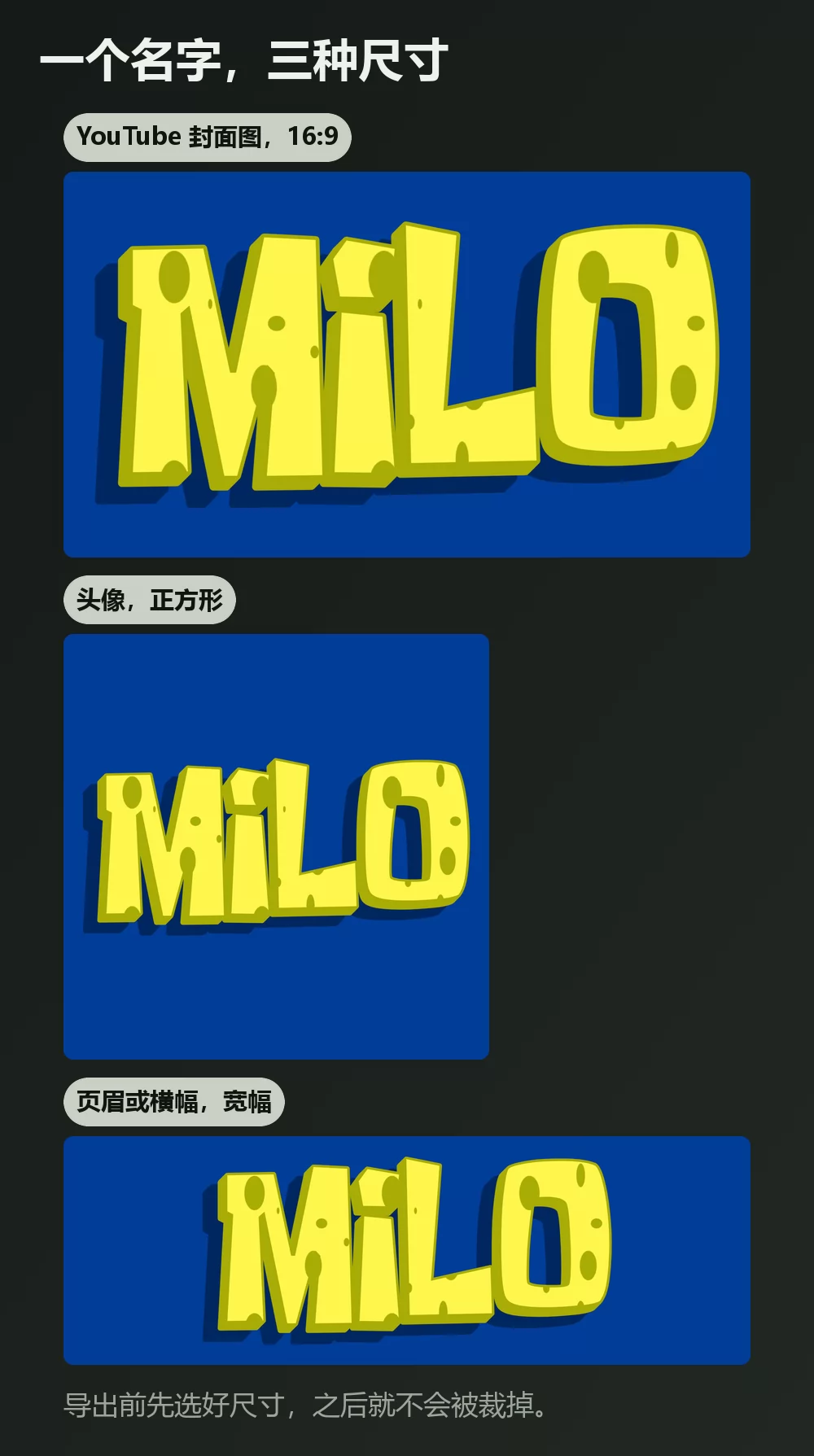
导出前先定好尺寸,之后就不会被裁掉。视频封面用 16:9,头像用正方形,派对横幅用宽条。
第 4 步:下载
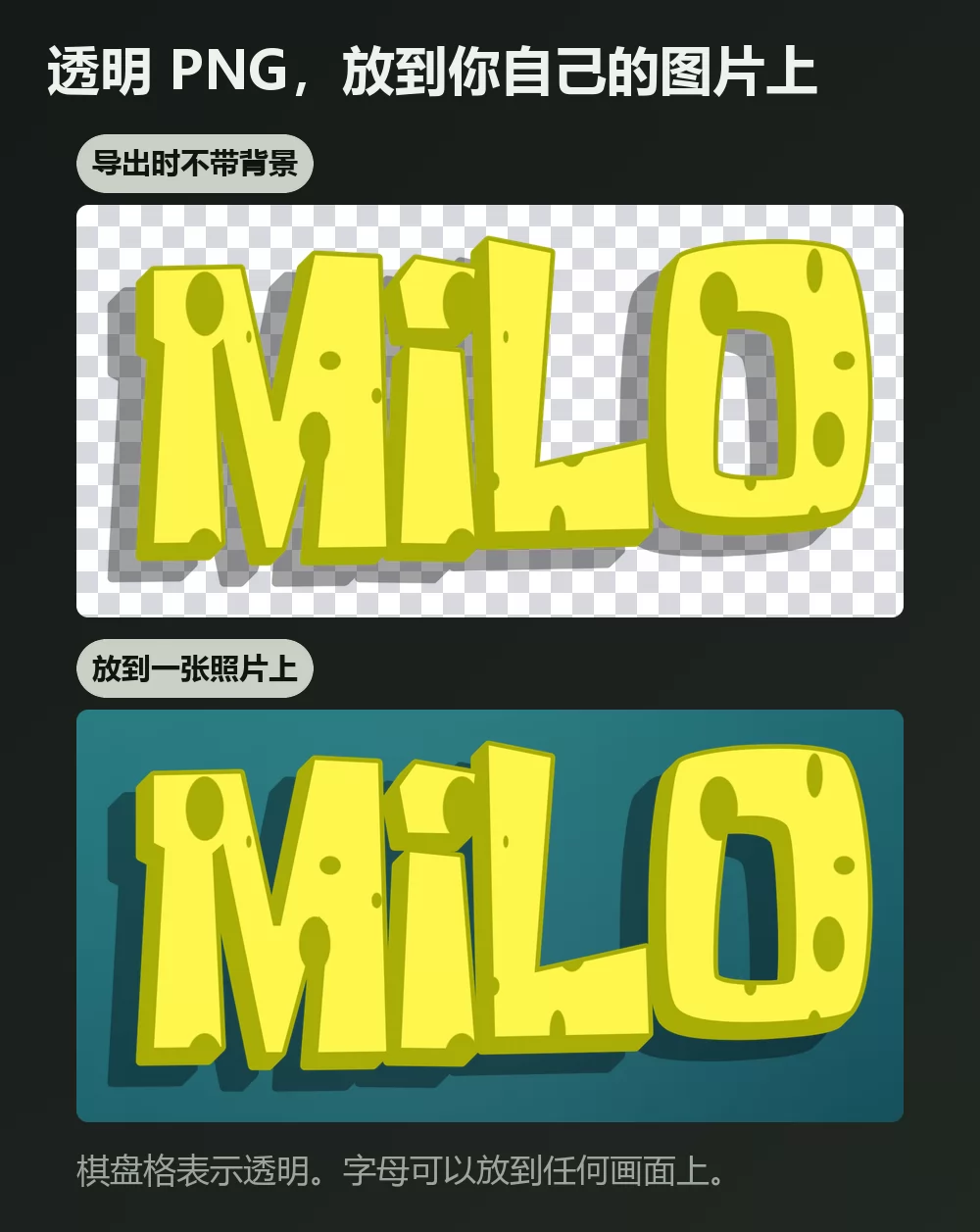
在「下载」标签里选透明 PNG,如果你打算把字母放到自己的照片、截图或邀请函上。这是大多数人漏掉的选项,也正是它让成品看起来是做出来的,而不是贴上去的。
名字一长,很快就占满宽度
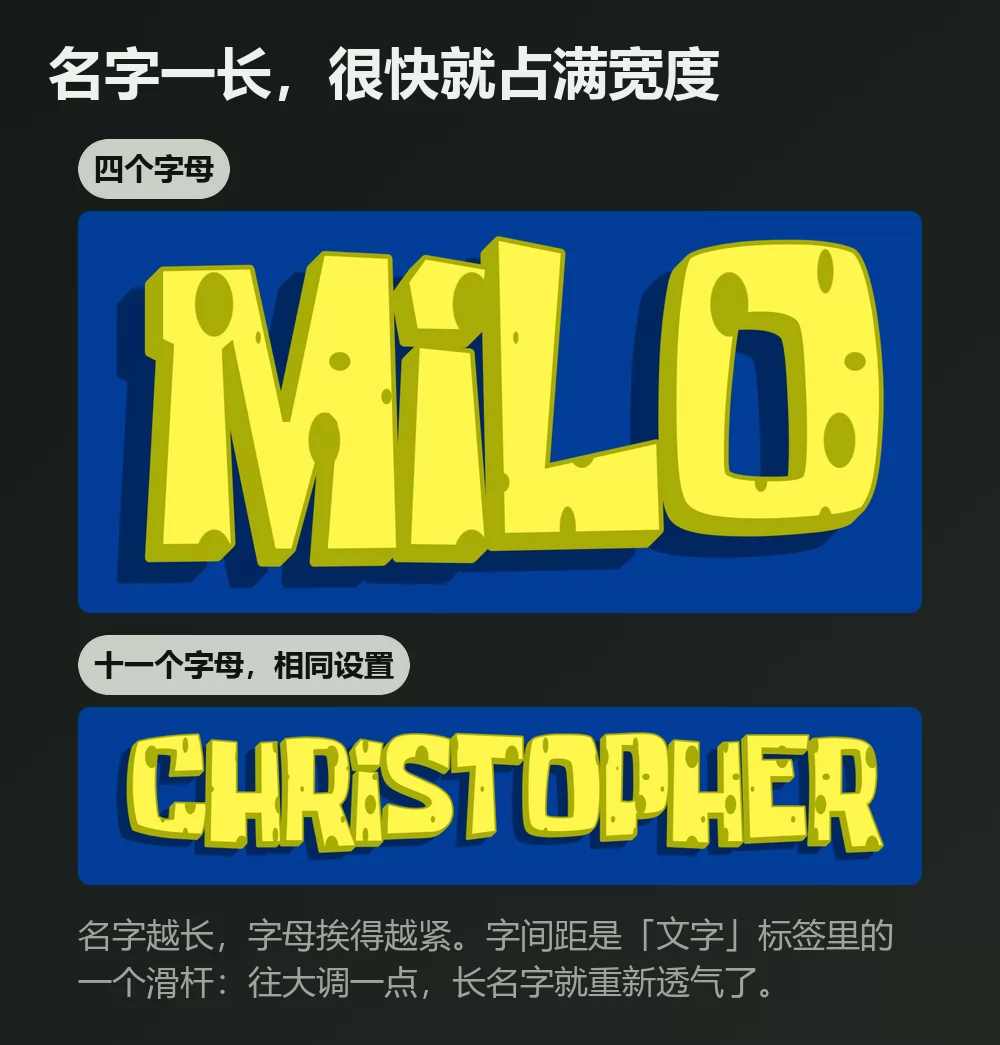
字母越多,挨得越紧。字间距是「文字」标签里的一个滑杆:往大调一点,长名字就不再显得局促。同一个标签里还有缩放、行高、弯曲和旋转。
两种风格,两种用途
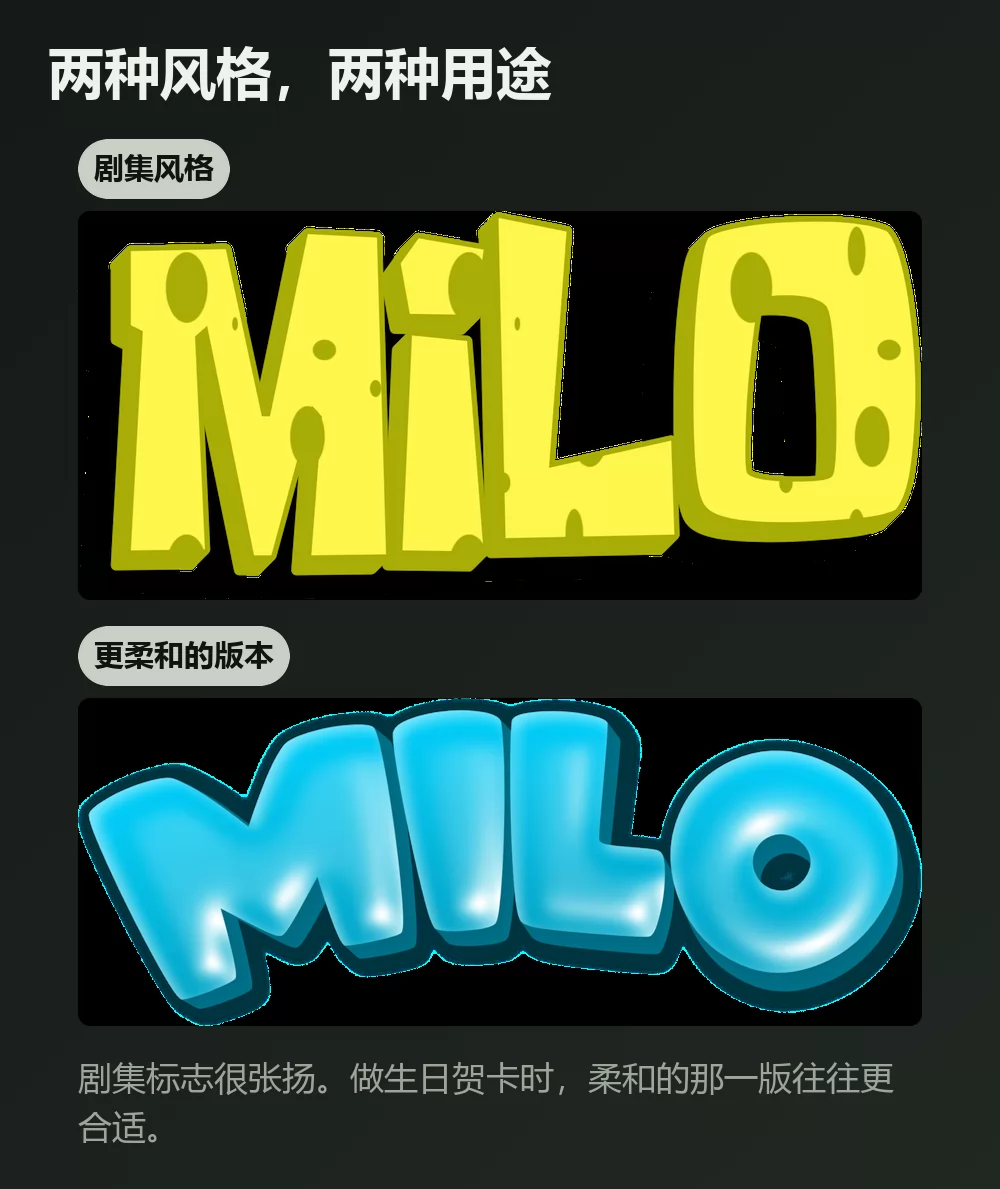
动手前先想清楚,因为它们适合的场合不同。
剧集风格适合封面图、海报,以及任何需要抢注意力的东西。
更柔和的气泡版本在生日贺卡或邀请函上通常更合适,因为剧集标志放在其他元素旁边容易显得吵。同样的思路,音量小一些。
如果你想装字体,该选哪一款
这个标志其实由两种字体组成,这也是为什么没有哪一次下载能完全对上。
「SpongeBob」是剧集创作者史蒂芬·海伦伯格为作品定制手绘的字,内部称作 Spongeboy TT1。它从未发布,所以所有免费的都是粉丝复刻。
「SquarePants」则是一款真正可以购买的字体:Las Vegas Jackpot,由 Ken Barber 为 House Industries 设计,大写 Q 的斜线被换成一道平直横杠。
下载量最高的那款复刻版,附带着作者本人的警告。 Seil 制作的 Krabby Patty 在 DaFont 上已超过 70.8 万次下载。作者说明字形是从低分辨率游戏贴图上自动描摹出来的,直言它放大后效果不佳,并指向 Spongeboy Me Bob 或 Some Time Later。文字小的时候够用;到了标题尺寸,自动描摹的痕迹就会显现,恰恰在字母最大的地方边缘变软、变得疙疙瘩瘩。
这也是标题该用生成器的诚实理由。字体给的是字母形状;海绵质感、气孔、描边和阴影都是叠在上面的效果。
在 Canva 里怎么做海绵宝宝文字
Canva 的字体库里没有海绵宝宝字体,免费版也不能自行安装。变通的做法是把字做成透明 PNG 再上传:它能直接放进 Canva 的设计里,而且依然清晰。
在 Photoshop 里怎么做海绵宝宝文字
装上 Krabby Patty 这类复刻字体,输入文字,然后用图层样式把这套处理重建出来:
- 描边,设为外部,用很深的蓝色或黑色,调厚一些。
- 颜色叠加用黄色,或者加一点渐变做出立体感。
- 投影,向下并向右偏移,范围收紧。
海绵上的气孔是字体给不了的。剧集里它们是画在每个字母内部的,要重现就得在上方图层画柔和的椭圆,再剪贴到文字上。
在 Word 里怎么做海绵宝宝文字
装上字体,输入文字,再用文字效果加描边和阴影。Word 的效果比图像编辑软件粗糙得多:凡是要打印的东西,导出的 PNG 都会比 Word 能做出来的好看。
在手机上
在 iOS 和 Android 上,大多数应用都无法安装并使用自定义字体。生成器可以在手机浏览器里跑,所以实际可行的路径是:在手机上做好 PNG,存到相册,再在你原本用的那个应用里添加进去。
常见问题
海绵宝宝标志用的是什么字体? 两种。「SpongeBob」是史蒂芬·海伦伯格的定制手绘字,从未发布;「SquarePants」是 House Industries 的 Las Vegas Jackpot,大写 Q 经过改动。
怎样做出海绵宝宝字体的文字? 在海绵宝宝文字生成器里输入,挑一个风格,下载 PNG。十秒钟,什么都不用装。
免费字体放大后为什么发虚? 这与制作方式有关。Krabby Patty 的作者自己说明,其字形是从低分辨率游戏贴图上自动描摹的,并推荐在较大尺寸下改用 Spongeboy Me Bob 或 Some Time Later。
怎样得到透明背景? 在「下载」标签里选透明 PNG,然后把字母放到你自己的图片上。
只靠字体能得到海绵上的气孔吗? 不能。气孔属于插画的一部分,不属于字母形状。生成器会替你加上;在 Photoshop 里则要在剪贴图层上自己画。